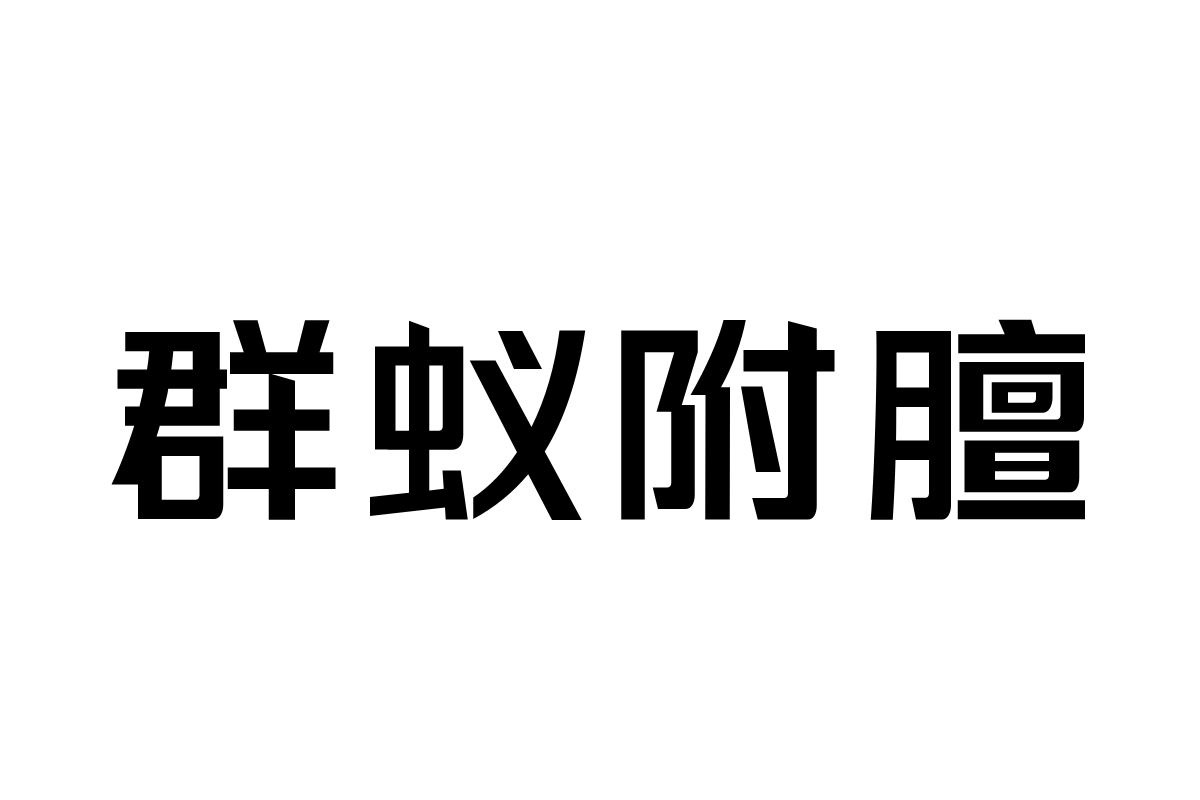
三极力量酷黑是一款粗体中文字型,具有强烈的视觉冲击力和辨识度。它的设计灵感来源于现代科技感和力量感,通过独特的字形结构和粗细搭配,展现出一种独特而时尚的视觉效果。
这款字体的特点是线条粗犷有力,给人一种强烈的视觉冲击感。同时,由于采用了粗体设计,使得整个字体更加醒目,易于识别。无论是在广告、海报、标题还是正文中,都能很好地突出主题,吸引观众的注意力。
三极力量酷黑的应用场景非常广泛,适用于各种需要强调文字信息的场景,如品牌宣传、产品推广、企业标识等。它不仅能够提升品牌形象,还能够增强信息的传递效果,让受众更好地理解和记住品牌或产品的特点。